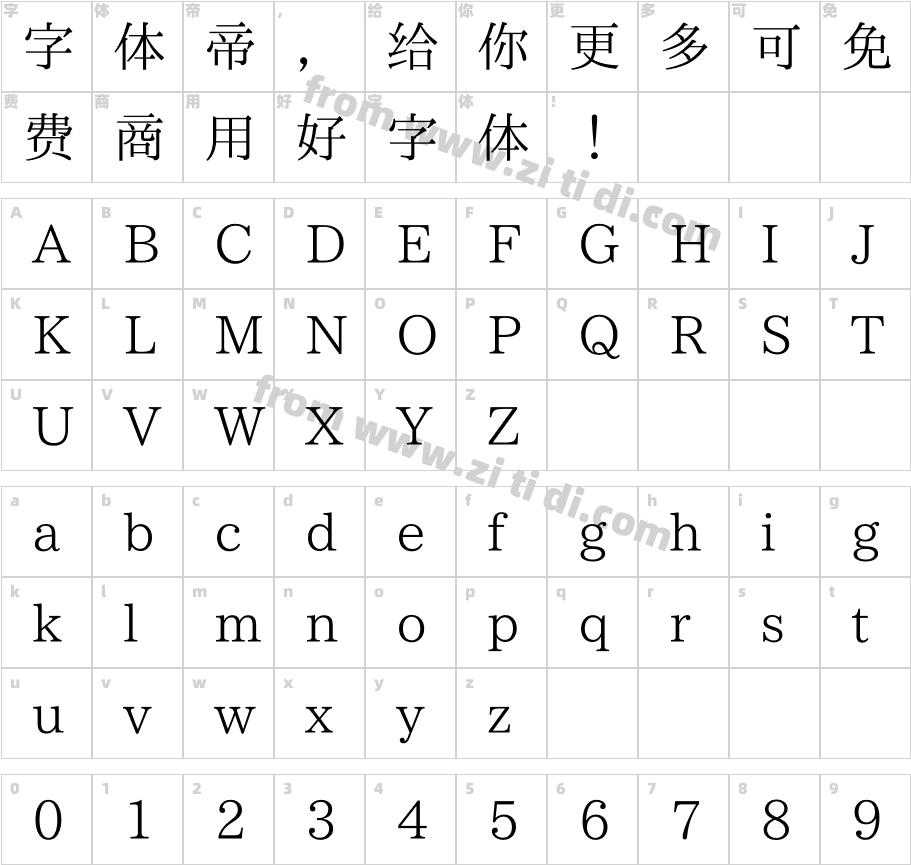
一点明体
字体风格: 明朝体
一点明体的前身是刻石录明体,已由开源字型组织I.字坊(一点字坊)全力维护。明朝体在我们中国其实就是宋体,只是日本、韩国等国家才称为明体或明朝体。
一点明体依照传承字形标准化文件《传承字形部件检校表》的推荐字形标准制作,力求遵从字理,展现传承汉字构字的科学系统。同时,我们另备“一点明体异体”,呈现传统印版字中常见的异体。
「I.明体」(I.Ming):收录力求遵从字理的传承字形。
「I.明体CP」(I.MingCP):与「I.明体」一样,唯全形标点置中。
「I.明体异体」(I.MingVar):部份汉字改爲收录一些也常见,但字理上未必比上者佔优的传承字形。
「I.明体异体CP」(I.MingVarCP):与「I.明体异体」一样,唯全形标点置中。